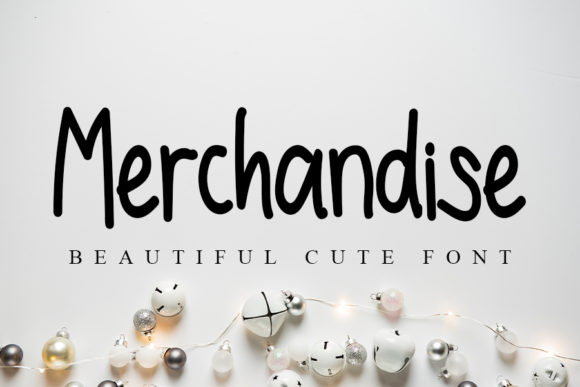
Merchandise
์˜ฌ๋ฐ”๋ฅธ ๋””์ž์ธ ์š”์†Œ๋ฅผ ์ฐพ๋Š” ๊ฒƒ์€ ์–ด๋ ค์šธ ์ˆ˜ ์žˆ์ง€๋งŒ Merchandise๋Š” ์ž‘์—…์„ ์ฆ‰์‹œ ํ–ฅ์ƒ์‹œํ‚ค๋Š” ๋›ฐ์–ด๋‚œ ์ปฌ๋ ‰์…˜์„ ์ œ๊ณตํ•ฉ๋‹ˆ๋‹ค.
POD(์ฃผ๋ฌธํ˜• ์ธ์‡„) ์ œํ’ˆ, ๊ฒฐํ˜ผ์‹ ์ดˆ๋Œ€์žฅ ๋˜๋Š” ์†Œ์…œ ๋ฏธ๋””์–ด ๊ทธ๋ž˜ํ”ฝ์„ ๋งŒ๋“ค ๋•Œ Merchandise๋Š” ์ด์ƒ์ ์ธ ์„ ํƒ์ž…๋‹ˆ๋‹ค.